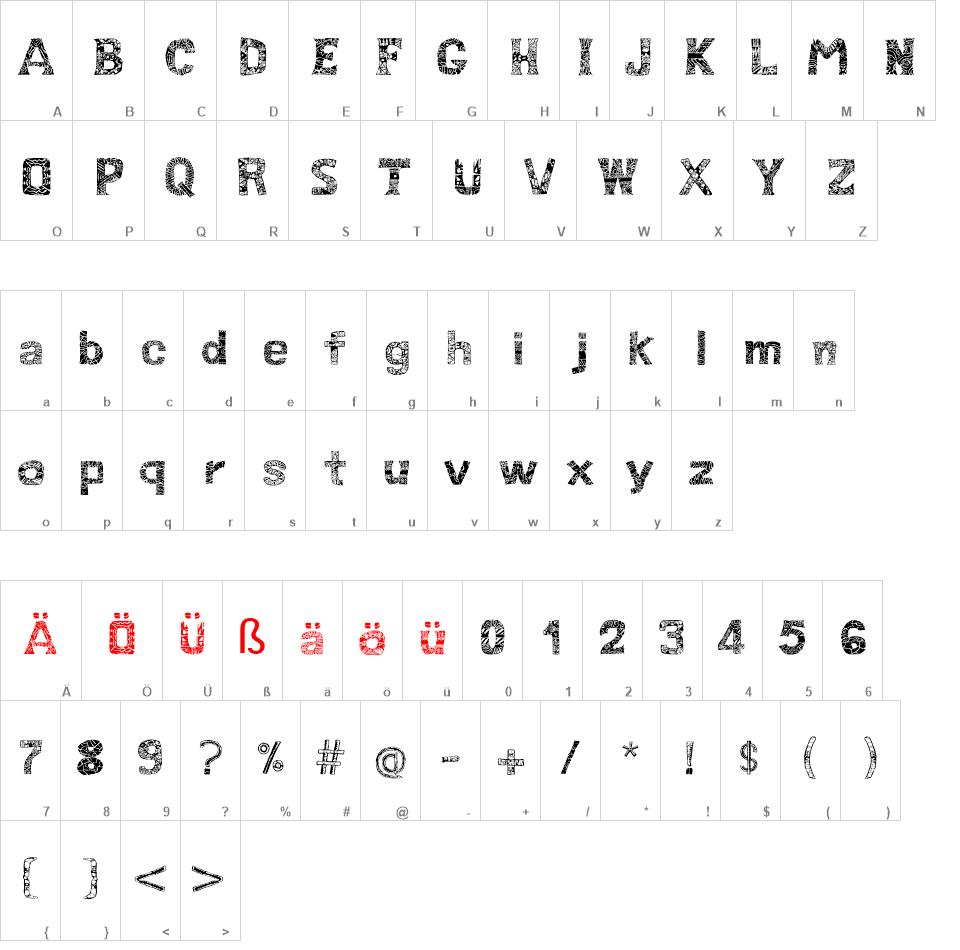
Maningue Staile
Maningue Staile font
Maningue Staile
A tipografia Maningue Staile contou com a participação de muitas pessoas de Moçambique, Portugal e Brasil. A técnica utilizada para a criação dos tipos foi o batik, em que o desenho é produzido por sucessivos tingimentos em tecido, protegido por máscaras de cera, onde somente as partes não vedadas pela cera são tingidas.
Este trabalho buscou pela linguagem que os artistas de rua da cidade Maputo utilizam para criar o design singular das figuras africanas presentes em suas obras. O batik de Moçambique retrata o dia a dia dos nativos, animais africanos, máscaras tribais, dentre outros signos locais.
Os 7 artistas que se dispuseram a executar este projeto são:
Nicolau Parruque, Miguel Cumaio, Sitóe, Macassa, Carlitos, Tovela e Sérgio. Todos eles moçambicanos, atuantes nesta cena local.
Os artistas foram livres para criar os caracteres, porém, tendo como regra obedecer uma proporção pré-determinada (cada caractere com aproximadamente 15 x 20 cm). Ao todo foram produzidos 45 batiks, com mais de 100 caracteres.
Cada caractere foi redesenhado digitalmente, sofrendo mínimas alterações para garantir a leitura do tipo, porém, sem deixar perder a originalidade deste trabalho artesanal.